TIPOGRAFIA 3D
Buenos días. Hoy les comparto un dibujo de texto en 3D, con el que puedes practicar si eres nuevo en illustrator.
Establecemos nuestra paleta de colores. Y con la herramienta de texto escribiré la palabra “Kadosh” de manera desordenada, como puedes apreciar en la imagen siguiente.
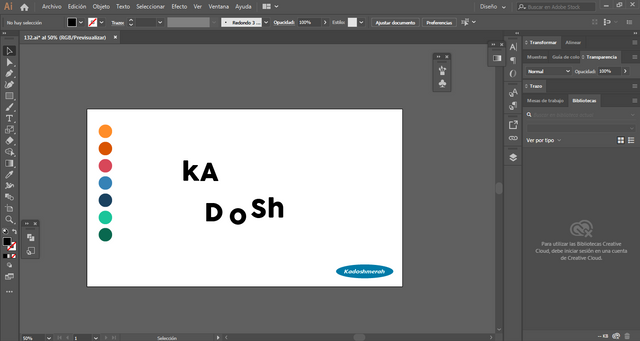
Aplicamos a las letras “K” y “A” un efecto 3D de extrusión y biselado el cual lo encuentras en el menú de efecto > 3D > extrusión y biselado.
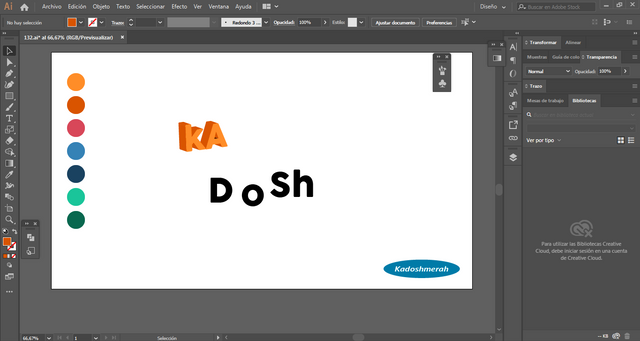
Igualmente extrusión y biselado para las demás letras rotando su angulo.
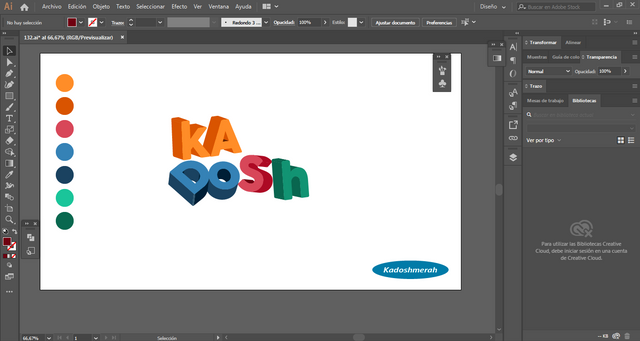
Aplicamos luces y sombras.
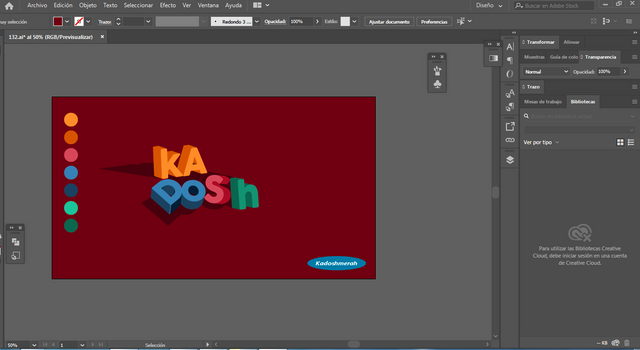
Aplicamos detalles de colores ayudados con la herramienta forma. Esto se los he enseñado en post anteriores.
Y listo.